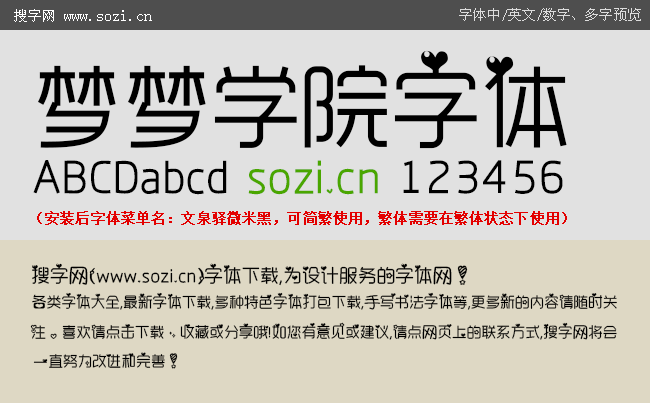
夢(mèng)夢(mèng)學(xué)院字體
搜字網(wǎng)給大家提供一款夢(mèng)夢(mèng)學(xué)院字體手機(jī)中文字體下載。這款手機(jī)字體是在文泉驛微米黑字體筆畫(huà)間插入了可愛(ài)的卡通圖案。文泉驛微米黑是一款應(yīng)用于藝術(shù)設(shè)計(jì)方面的中文簡(jiǎn)體漢字,又名文泉驛等寬微米黑,該字體偏粗,字形大方得體,加入了卡通圖案后增添了趣味性,特別適合喜歡手機(jī)字體個(gè)性一些的朋友在手機(jī)上安裝使用。